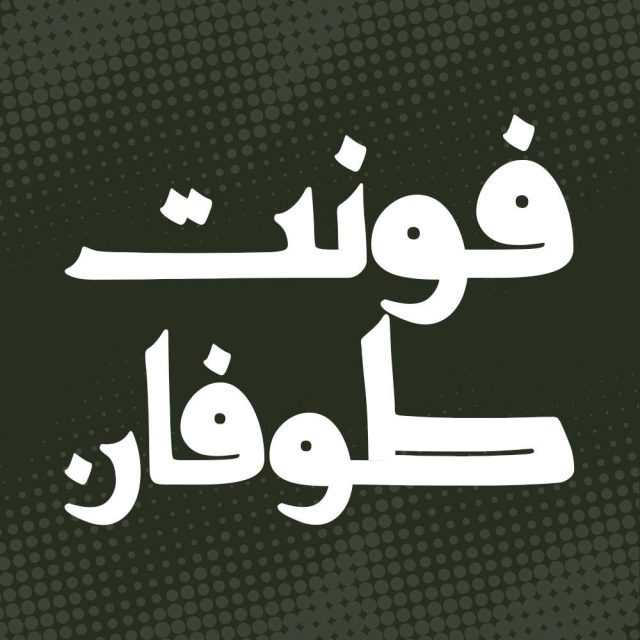
فونت فارسی طوفان Toufan Font
فونت طوفان به دلیل وزن بالایی که دارد جهت استفاده در عناوین، تیترها و بخش‌ های مهمی از متن که قرار است برجسته و بزرگ باشند…
فونت طوفان به دلیل وزن بالایی که دارد جهت استفاده در عناوین، تیترها و بخش‌ های مهمی از متن که قرار است برجسته و بزرگ باشند مناسب است. از جمله ویژگی‌ های مهم فونت طوفان می ‌توان به ضخامت بالای کلمات، برجستگی و جذابیت ظاهری اشاره کرد. علاوه بر این، این فونت چون وزن بالایی دارد اگر در متن ‌های بلند مورد استفاده قرار گیرد، ممکن است باعث خستگی چشم شود. پس بهتر است شما عزیزان از این فونت برای نگارش متون کوتاه و بخش ‌هایی که قرار است برجسته باشند، استفاده کنید. در ادامه برای شما نمونه تایپ های این محصول حرفه ای رو آماده کردیم که میتونید مشاهده کنید.
• مناسب طراحی بسته بندی ها و چاپ
• فونت ویژه تبلیغات محیطی
• فونت طراحی کاور اینستاگرام
• فونت حرفه ای برای تولید محتوا
• فونت فارسی طراحی وبسایت
• فونت طراحی لوگو تایپ فارسی
• مناسب استفاده در تابلو های چلنیوم و طراحی حروف
پیشنمایش و نمونه تایپ های فونت طوفان